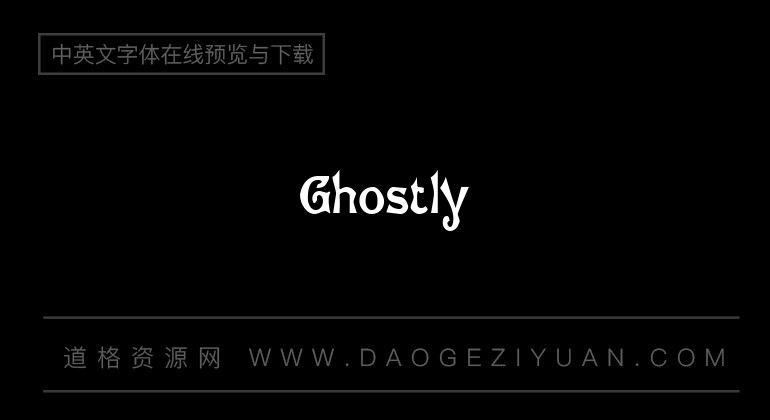
Ghostly 字体是一款由 Ghostly International 公司推出的字体,它是一种自由、抽象的设计,具有现代感和个性。它的特点是简洁而有趣,拥有细节丰富的字形,可以用来创造高度可读性和复杂的设计。它的主要应用领域是电子音乐、街头艺术、品牌标识和印刷品等。内容介绍
Ghostly是一款非常不错的手写艺术字体,具有很好的视觉感,适合于文化类的宣传设计、商业类品牌的广告和产品包装设计以及个性化文字排版等较多场景。